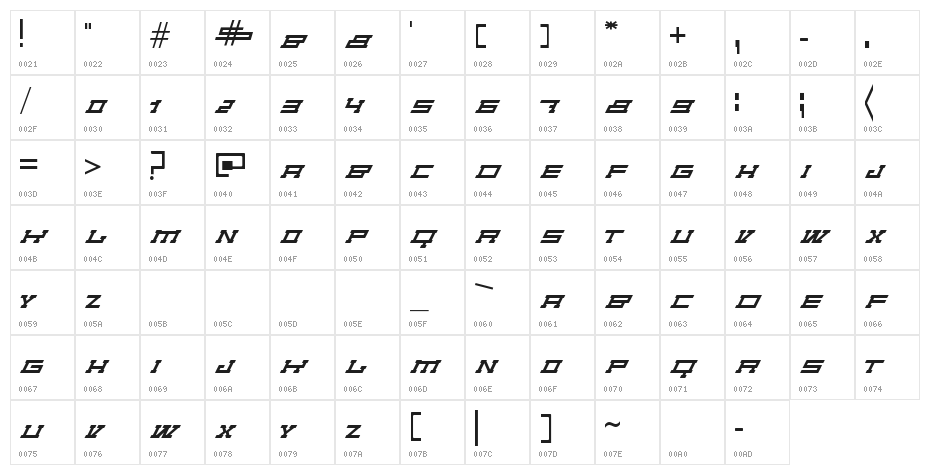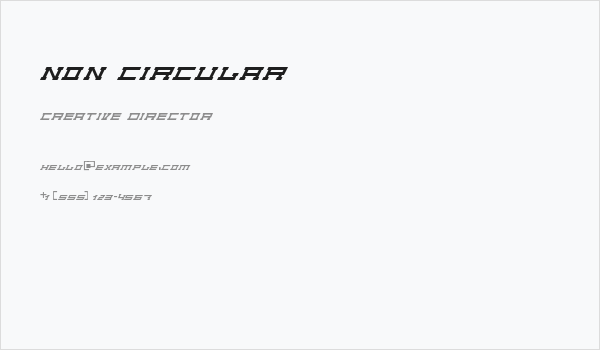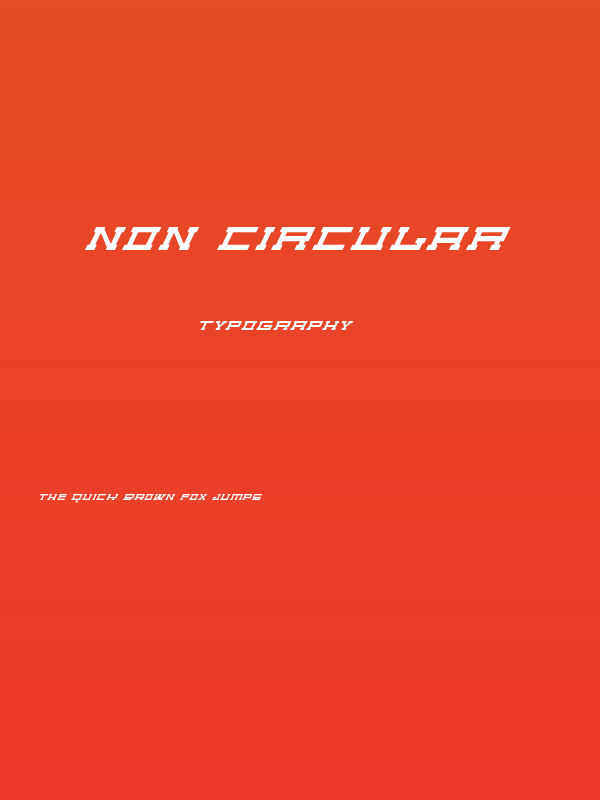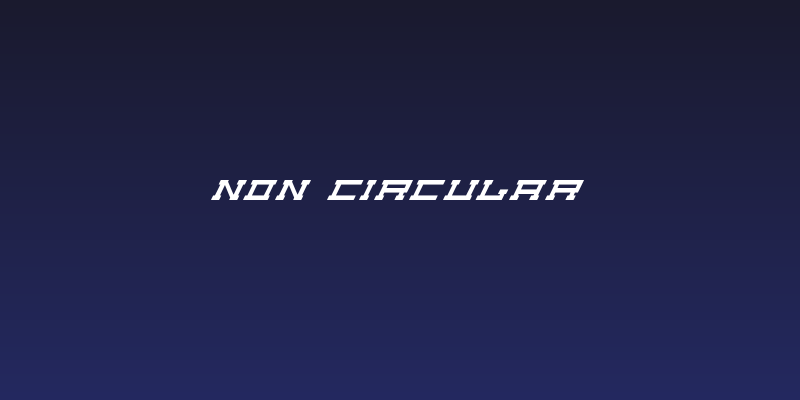
Non Circular Font
✎ Futuristic
| Gesamtstil | Futuristic |
| Anwendungsfall | Logos, Headlines, Posters |
| Vorgeschlagene Projekte | Ideal for sci-fi themed designs, video game graphics, technology branding, and modern posters. |